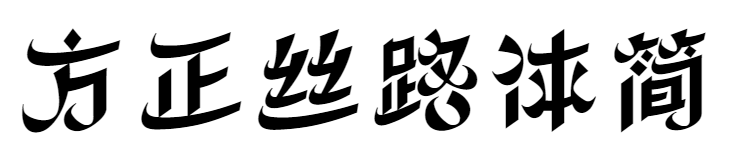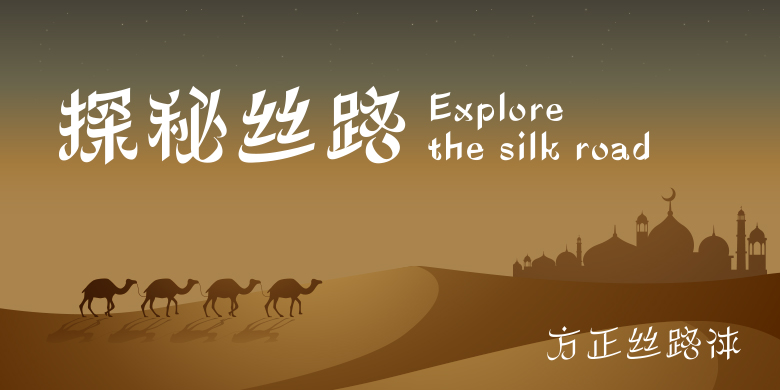
方正絲路體系列字體共8款
絲路體設計是從已有的字庫成品方正藏意漢體得到啓發,把新疆維吾爾族使用的阿拉伯文字,作爲此次創作的出發點。 絲綢之路,阿拉伯文化與漢文化的交流之路,融合之路。絲路體,借古開今,抛磚引玉。 美學方面,維吾爾族在生活中熱愛舞蹈。在設計中因字制宜,圍繞動態奔放做了稍誇張的表達,保證識別度的同時,賦予特有的情感訴求。 筆畫方面,阿拉伯文字有著自己特有的造型特征,常用扁筆書寫。如撇和捺的折筆處、收尾處,需要靈活掌握幅度、大小,這些都會影響整個字的氣質與態勢;還有豎筆、撇筆,爲了追求與阿拉伯文字筆畫的起筆收筆壹致,在筆畫橫豎交叉的地方做了氣口的處理。 期間請了不同的老師、朋友看,也請了維吾爾族美術老師提了建議,形成了目前的面貌。難點在于,組構後的阿拉伯韻味與字庫字體需具備的快速識別性之間的平衡。 作爲排版字體,犧牲了壹定的阿拉伯文字的筆畫特征。適合用于書、報、刊、屏幕等媒介閱讀使用的標題、正文字體。設計師: 劉和存發行時間:2018字庫編碼:大陸簡體(GB2312-80)、簡繁擴展(GBK)關鍵詞:最新字體、系列字體、特粗的、創意字體